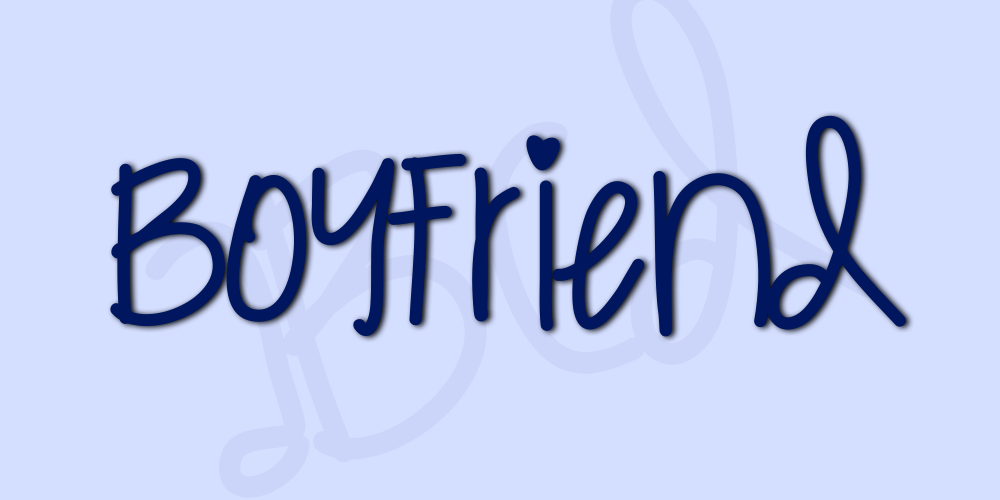
Boyfriend font – Fonte Grátis
Boyfriend font
Aqui está uma breve descrição envolvente para a página de download da font ‘Boyfriend’: Na categoria de Script Fonts, encontrará uma elegante e única font que carrega consigo um ar romântico e quente. Inspirada na natureza do amor mais puro entre amigos e casais apaixonados, a font Boyfriend é perfeita para criar mensagens leves e descontraídas. Com um design cuidadosamente criado em 2015 pelo designer Hamilton, essa font expressa com simplicidade e elegância sentimentos íntimos. Se você está procurando uma maneira de capturar o espírito romântico da comunicação digital, a font Boyfriend é perfeita para tornar suas mensagens ainda mais autênticas. Para aqueles que desejam adquirir um licenciamento desta maravilhosa font, Hamilton está esperando para ajudá-los a enriquecer seu design com este toque especial e único. Combinada com as cores suaves do amor ou uma mensagem leve de carinho, esta font é certamente um must-have na sua coleção de recursos gráficos.